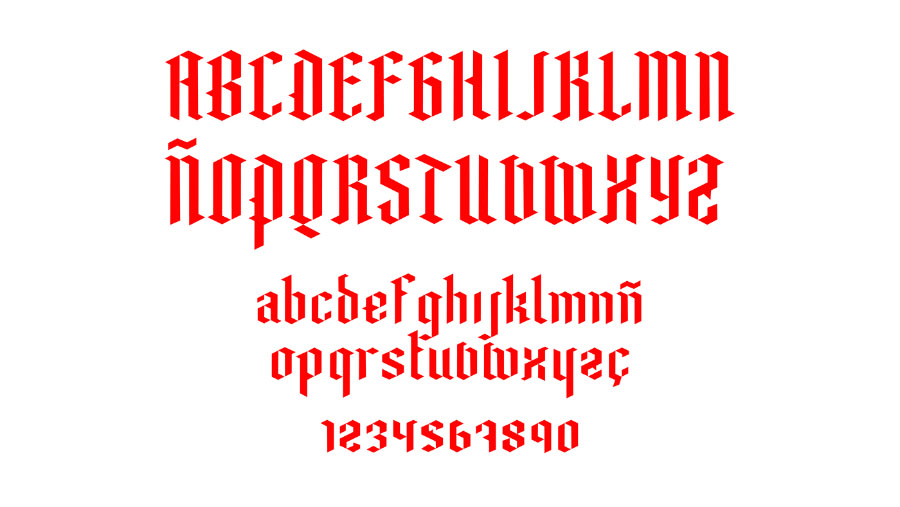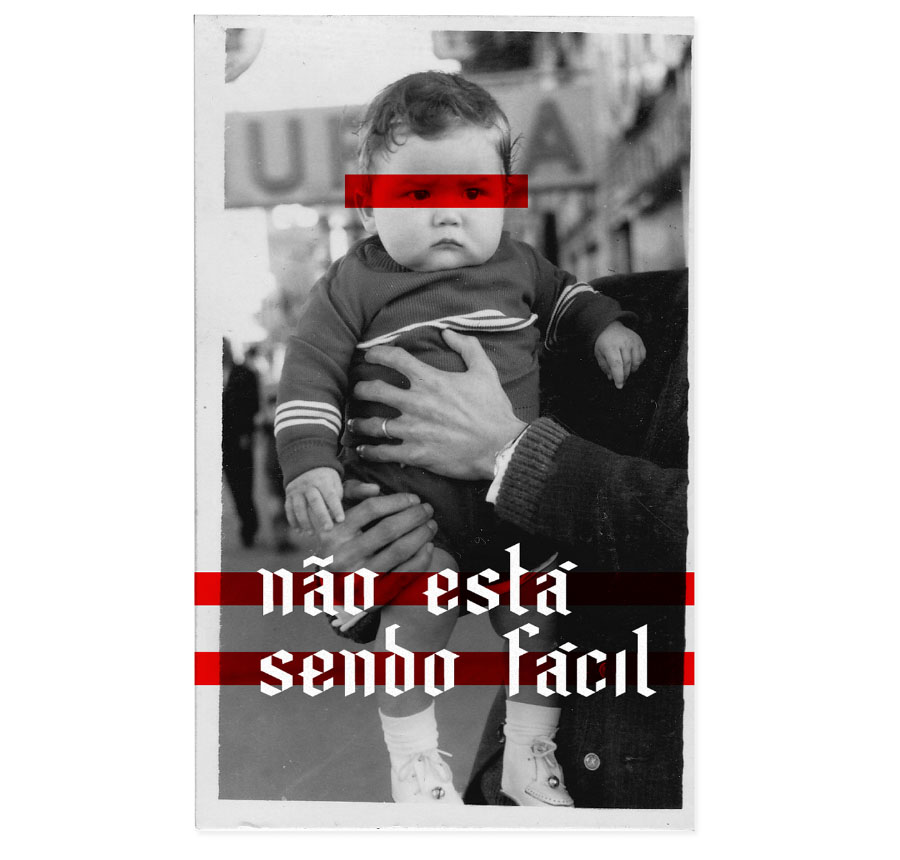
圣地亚哥黑字免费字体
圣地亚哥黑字免费字体是一个几何哥特式显示字体。这是从克里斯蒂安·洛佩斯(CristianLópez)的第一本和最新的作品中找到你的。这是老式的,但它符合现代设计的需要,它需要复古blackletter。因此,圣地亚哥在服装设计,品牌推广,产品包装,专辑封面,海报等等方面都会很棒!